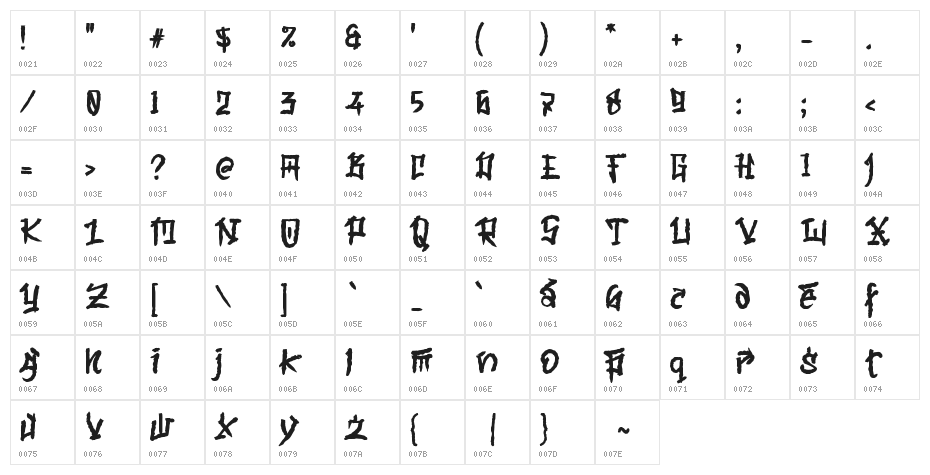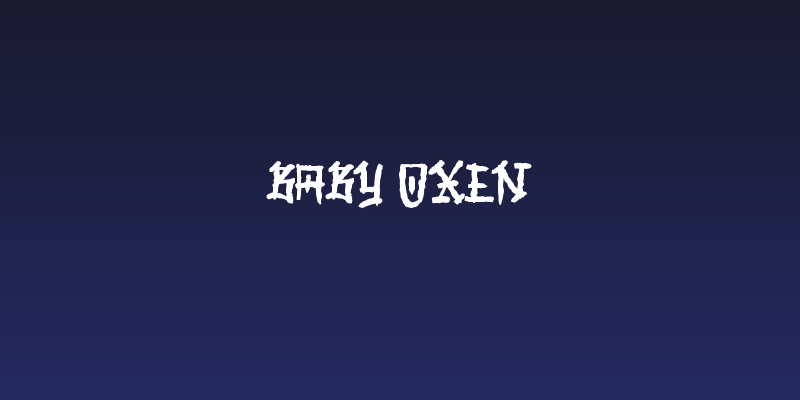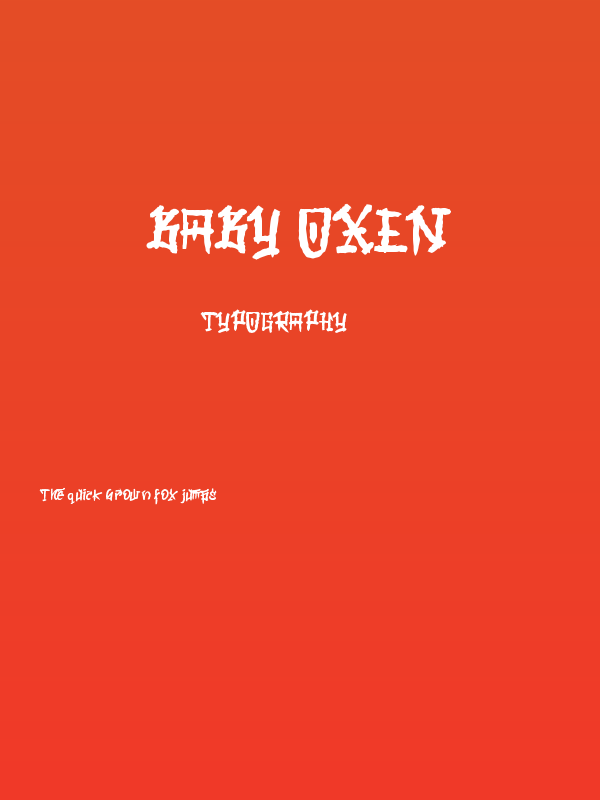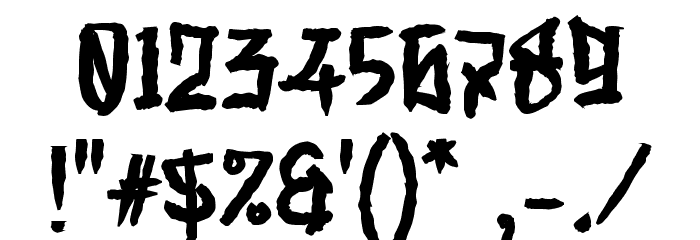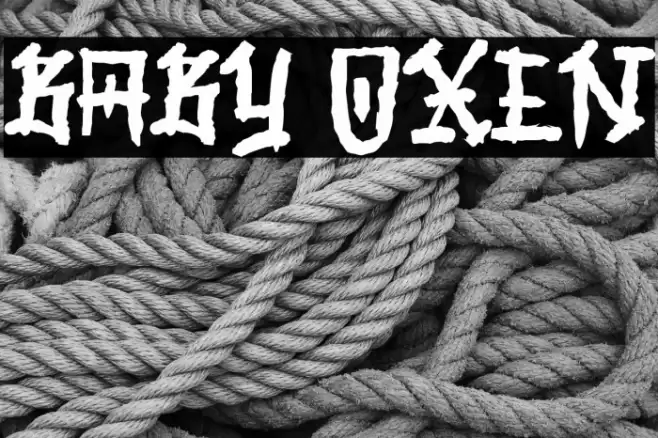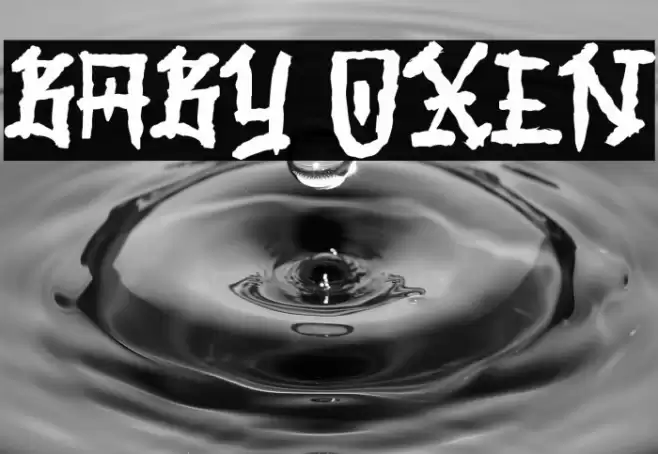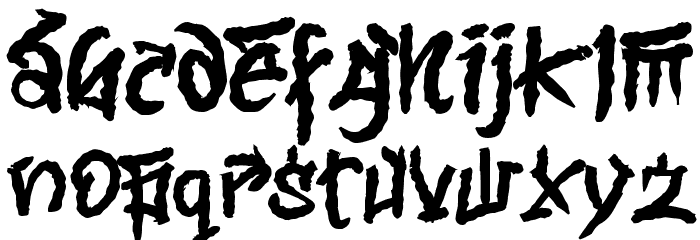
BABY OXEN Font
| Projets proposés | Perfect for album covers, posters, branding for edgy or alternative products, and any design needing a bold, artistic touch. |